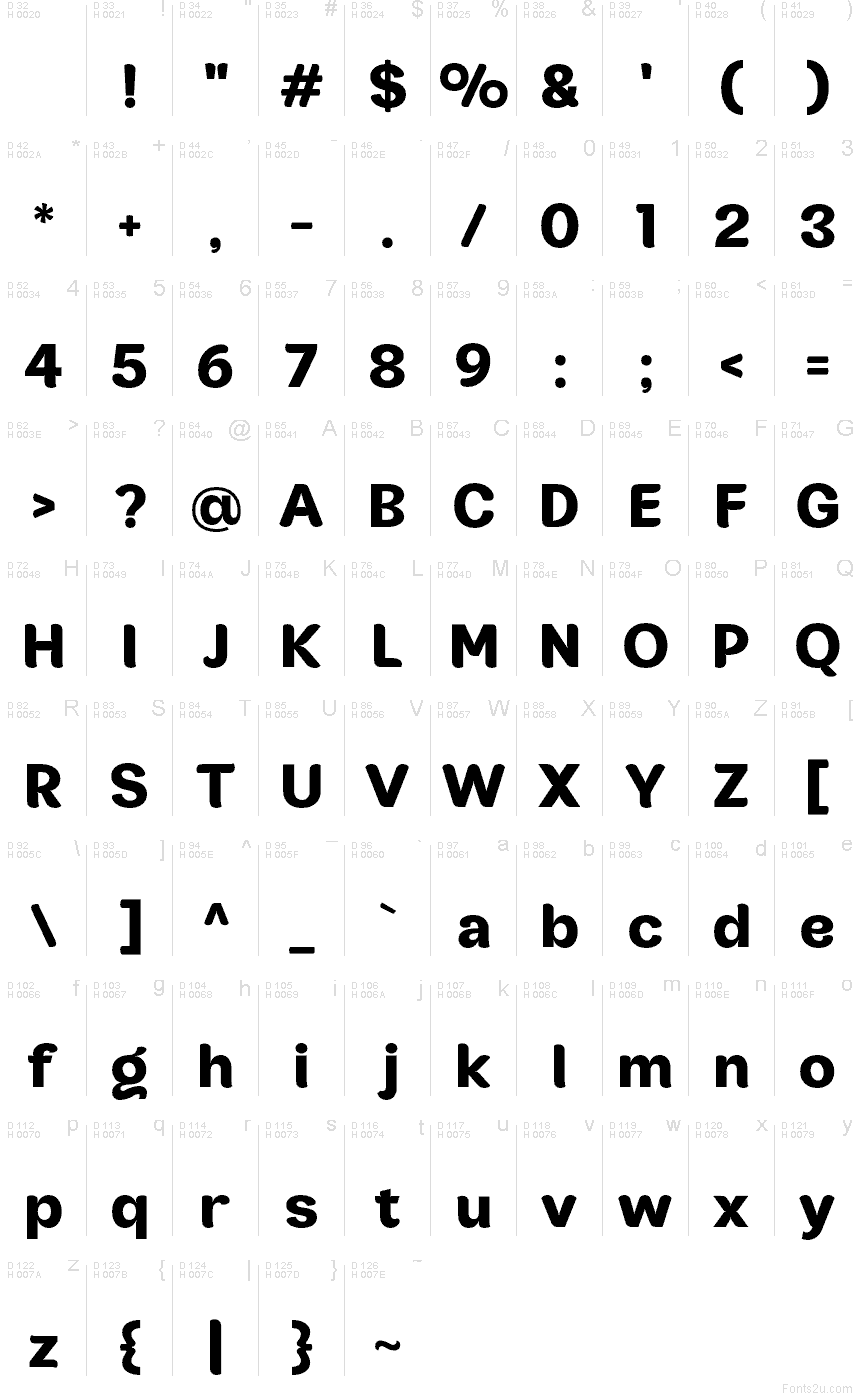
JHC Rasbora Extrabold, da Jehoo Creative, é uma fonte display moderna e gratuita, com letras grandes de bordas suaves e uma confiança robusta, quase retrô. As curvas pesadas, os ganchos profundos e as junções arredondadas dão à fonte um ritmo visual amigável, enquanto o espaçamento compacto a mantém com uma aparência ousada, em vez de apenas lúdica.
Ela se encaixa perfeitamente em branding, embalagens, arte de álbuns, menus de café e títulos de revistas onde frases curtas precisam de presença sem parecer rígidas. Por ser uma fonte gratuita, também é ideal para cartões de título, esboços de logotipos e cabeçalhos de redes sociais, já que o seu peso arredondado confere uma solidez gráfica mesmo em poucas letras.